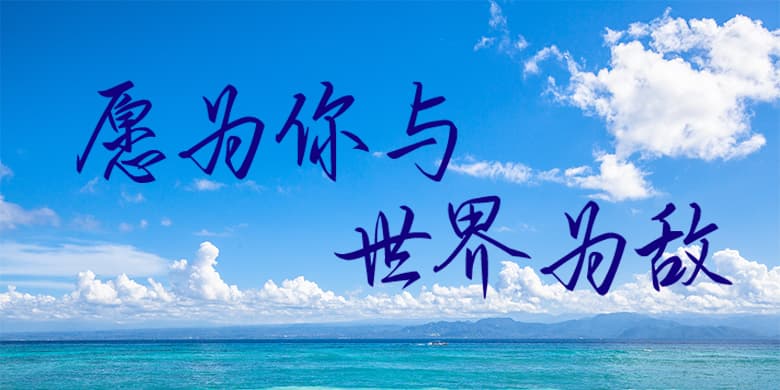
品牌:方正手迹设计师:刘殿儒发行时间:2020字库编码:简繁扩展(GBK)分类:常规书写·硬笔字体属性:精品字
这款体行笔劲健爽利,锋芒毕露,洒脱飘逸,具有很强的视觉冲击。而字形娟秀隽永,中宫收紧,结字严谨,承自传统书法,格调高雅又不失现代感。适用于现代诗歌、短文的排版以及文化、商业类品牌的广告语设计。